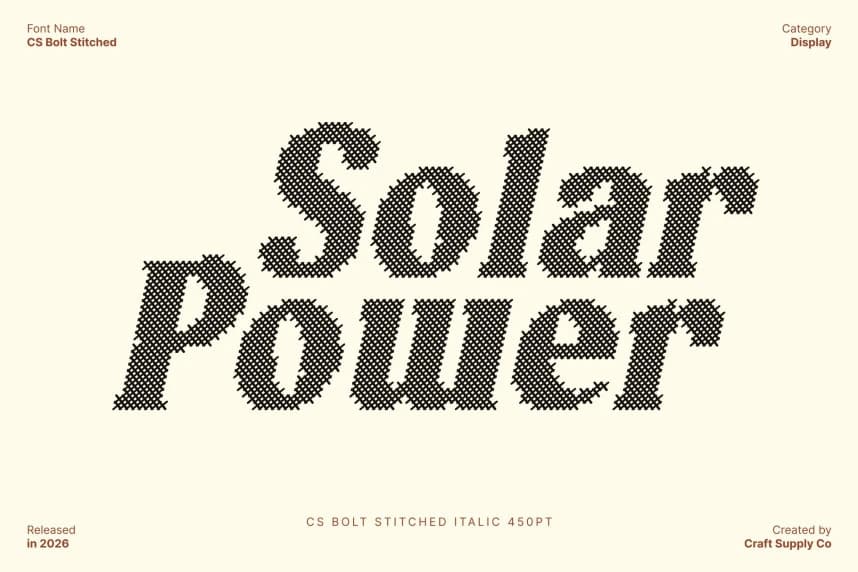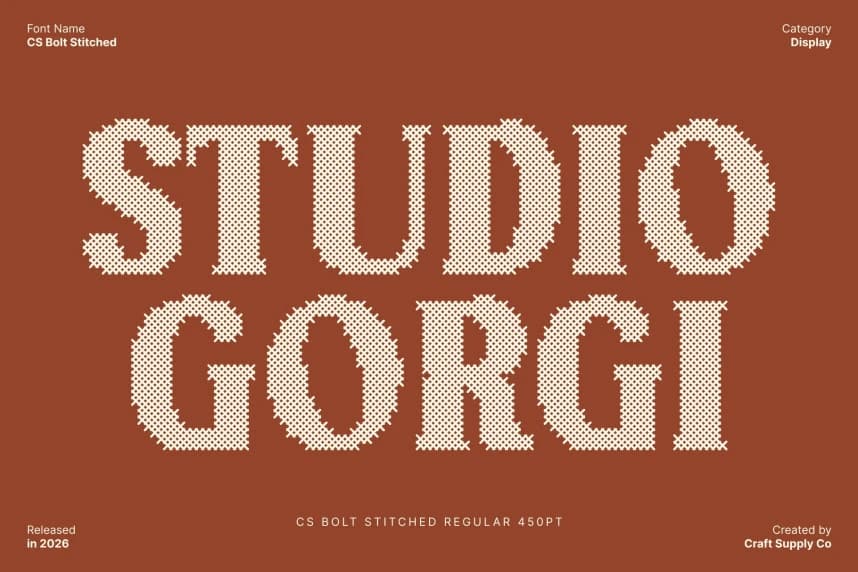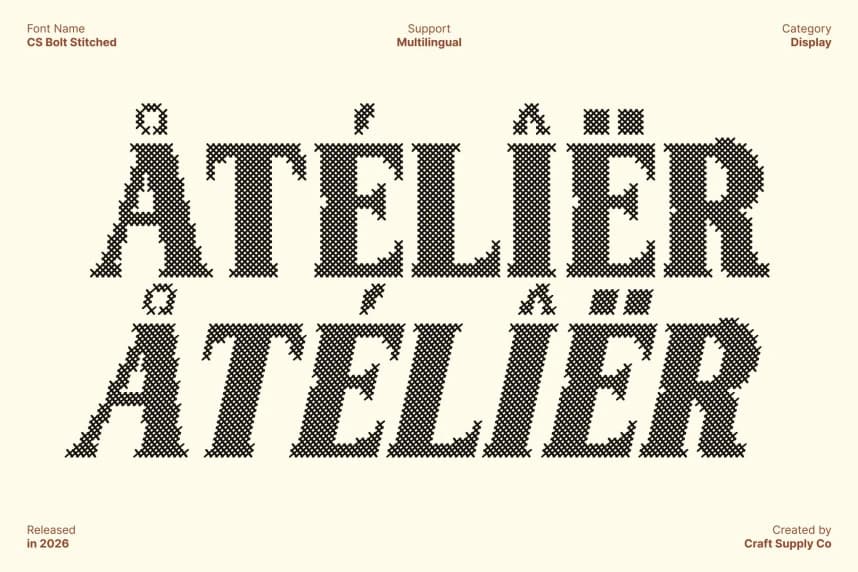
CS Bolt Stitched Font
CS Bolt Stitched Font – Kendinden emin modern güçle dolu Kalın Serif; El yapımı karaktere sahip Kalın Serif. Bu, güçlü ağırlık ve kendinden emin yapı ile dikkat çekmek için tasarlanmış bir kalın serif yazı tipidir.
CS Bolt Stitched Font – Kendinden Emin Modern Güçle Kalın Serif; El Yapımı Karakterli Kalın Serif. Bu, güçlü ağırlık ve kendinden emin yapı ile dikkat çekmek için tasarlanmış bir kalın serif yazı tipidir.